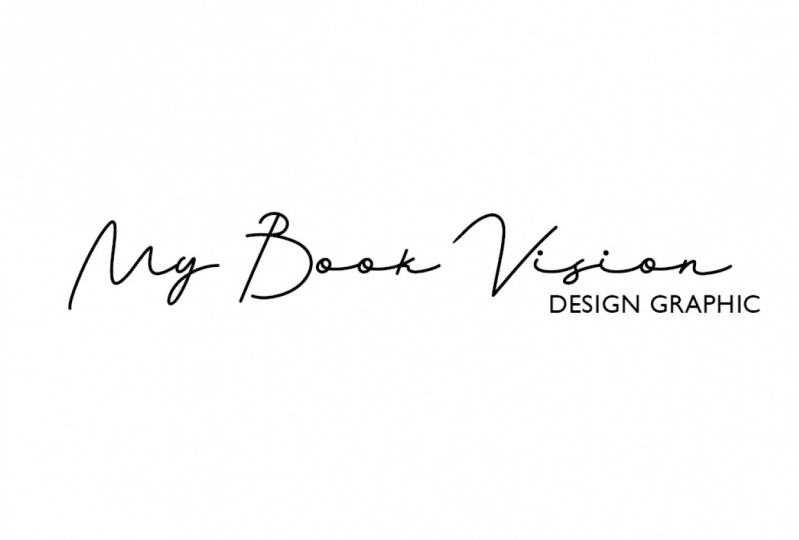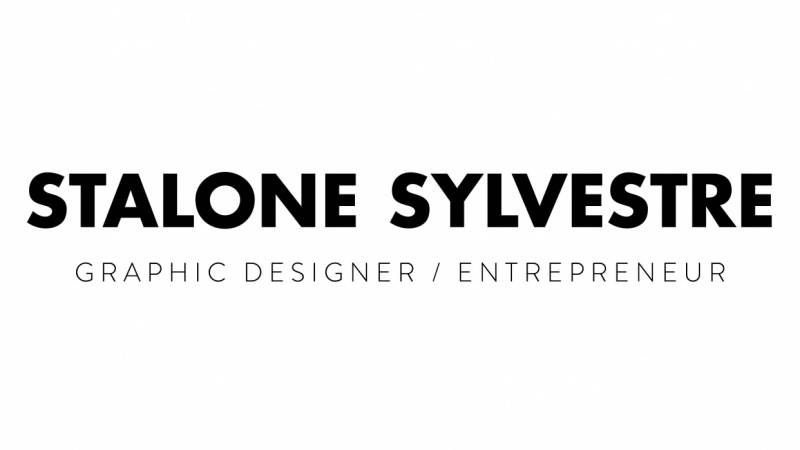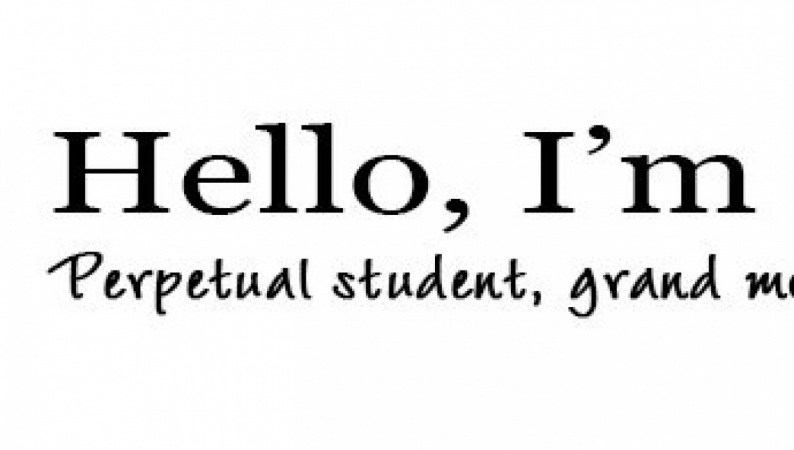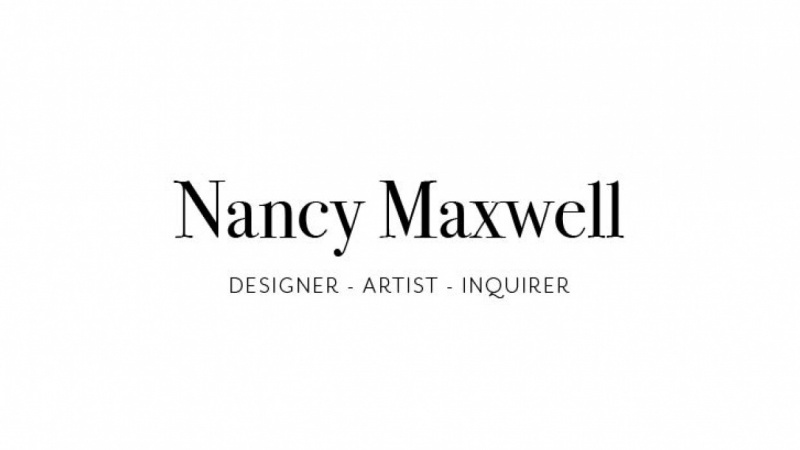
Dominando a tipografia 1: introdução ao contraste tipográfico
Apresentação e visão geral da série
Encontre algumas palavras para se apresentar
Crie designs impressionantes com contraste tipográfico
A tipografia é um dos principais componentes do design gráfico, e cometer erros é muito fácil. Mas também não é tão difícil acertar e fazer algo incrível! Nesta série vou explicar passo a passo todos os diferentes aspectos da tipografia e criar layouts eficazes que impactam o visitante. Amo uma boa tipografia e quero ver mais disso por aí.
Meu nome é Evgeniya Righini-Brand e sou uma designer gráfica com uma experiência extensa no trabalho com tipos em vários níveis diferentes e ensinando tipografia de nível universitário.
O que você vai aprender neste curso:
Neste curso, vamos dar uma olhada nos conceitos básicos da tipografia, princípios de contraste tipográfico e na seleção e combinação de tipos de fontes para transmitir a mensagem desejada. As habilidades de estilo que você vai obter através deste curso lhe permitirão fazer um trabalho simples baseado em texto e destacá-lo, seja ele uma apresentação, criação de uma página de título para seu trabalho acadêmico escrito ou a criação de imagens cativantes de capa para seus cursos ou projetos aqui na Skillshare ou em outras plataformas redes sociais.
A parte técnica desse curso abrange conceitos básicos de trabalho no Adobe InDesign, mas se você não tiver o InDesign instalado, não deixe de se inscrever, porque você pode praticar a composição tipográfica e as habilidades relacionadas ao estilo ensinadas neste curso no Adobe Illustrator, Photoshop ou qualquer processador de palavras padrão, como o Pages, Word ou até mesmo no Google Docs.
1. Apresentação e visão geral da série: Ei pessoal, isso é [inaudível] criativo. Bem-vindo à minha nova série sobre dominar a tipografia, na qual passarei passo a passo por todos os diferentes aspectos da tipografia, criando layouts eficazes e trabalhando de forma eficiente no Adobe InDesign, que é a minha principal escolha quando se trata de projetando este tipo. Se você quiser aprender do zero ou melhorar as habilidades existentes do InDesign, ótimo e se você não tiver a instalação do InDesign. Bem, não é o fim do mundo, porque muito do que eu vou cobrir nesta série é sobre estilo. Você pode experimentar a configuração de fonte no Adobe Illustrator Photoshop, ou mesmo em qualquer processador de alimentos padrão, se souber onde estão as ferramentas e o que deseja alcançar. Nesta série de aulas é realmente sobre a construção dessa compreensão de consciência. Todos os projetos de classe que serão configurados para você nesta série serão rápidos e divertidos e permitirão que você pratique novos aspectos da tipografia abordados em cada aula e produza algo útil que você pode expandir quando aprender mais. Na primeira aula, vamos começar aprendendo os conceitos básicos de tipografia, princípios de contraste topográfico e selecionar um tipo aparente de faces para refletir nossa personalidade. Vamos criar um crachá e crachá ou um cartão de introdução para nós mesmos, que no futuro você pode levar mais longe e desenvolver seu cartão de visita ou chefe de seu site ou blog. Por enquanto, apresente-se com estilo à comunidade aqui e em qualquer outra rede social, se quiser. Existem habilidades relacionadas que obtemos desta turma, lhe permitirão enfrentar eficazmente e fazer sobressair qualquer trabalho simples baseado em texto, seja uma apresentação, configurando a página de título para o seu trabalho acadêmico escrito ou fazendo imagens de capa cativantes foram aulas para projetos aqui em compartilhamento de habilidades ou em outro lugar nas redes sociais. Fico sempre feliz em responder a quaisquer perguntas, fornecer feedback e apoiá-lo a cada passo do caminho. Como eu já disse, se você não tem o InDesign, você pode definitivamente seguir essa classe e fazer o projeto de classe em qualquer outro software, então não deixe o software ficar entre você e aprendizagem como criar projetos tipográficos eficazes. Adoro conhecer novas pessoas e vou ficar muito animado para vê-lo na minha aula e ver como você pode se apresentar por meio de tipografia. 2. Interface e ferramentas básicas do InDesign: Vamos começar com os conceitos básicos de trabalhar no InDesign. Vamos criar composições tipográficas muito simples para esta classe. Então eu só vou cobrir aqui o que você vai precisar nesta fase, e eu vou expandir sobre isso em minhas futuras aulas da série. No Adobe InDesign, vá para o menu “Arquivo”, “Novo”, “Documento”. Agora, vamos preparar tudo rapidamente. Vamos compartilhar nosso trabalho on-line, então faz sentido definir a Intenção para Web e se você quiser desenvolvê-lo ainda mais para impressão, você sempre pode alterá-lo mais tarde. Por enquanto, vamos manter o número de páginas para um. Vamos trabalhar em diferentes designs do mesmo texto, então vamos apenas copiar páginas de dentro do documento à medida que avançamos para produzir diferentes variantes. Vamos trabalhar em páginas individuais em vez de espalhadas, por isso certifique-se de que as Páginas Viradas estão desativadas. Lembre-se sobre essa opção na configuração do documento. Na minha experiência, é algo que as pessoas esquecem facilmente. Se você precisar de uma simples apresentação ou documento de uma página ou slide de cada vez, não use Páginas opostas. Mas se você estiver trabalhando em algo semelhante a um livro que tenha duas ou mais páginas na página espelhada, então você precisará ativar as Páginas opostas. Vamos definir o tamanho da nossa página para algo como 1200 por 1200 pixels, isso é bastante grande um quadrado e por isso não temos distração pelas proporções da página e seria de boa qualidade quando exportamos para postar online. Então vamos ter apenas uma coluna aqui, não precisamos de mais para esta tarefa. Certifique-se de que você está alterando todas as margens ao mesmo tempo, clique neste botão de link para tornar todas as configurações iguais e defina margens como 100 pixels. Não precisamos fazer nada com configurações de Sangramento e Slug para esta classe, pois não estamos imprimindo. Então aqui estamos, clique em “Ok” para criar um novo documento. Vamos salvar imediatamente este documento para que não precisamos preocupar com isso mais tarde e basta clicar em “Salvar” ou “ Command S” ou “Control S” no Windows de vez em quando enquanto estamos trabalhando para que nosso arquivo seja sempre copiado. Trabalhando com o InDesign, é muito importante estar bem organizado para que você não perca nenhum material usado no documento. Nesta classe, nós não vamos ter nenhum arquivo vinculado, então nada com que se preocupar realmente, mas ainda é uma boa prática ter uma pasta separada para o projeto e um nome pesquisável para o arquivo. termos de formato, estamos salvando um formato de documento nativo do InDesign e, aqui, você pode ver que não há muitas opções de formatos para escolher de qualquer maneira. Documento do InDesign, que é o que é usado na maioria dos casos, formato de modelo do InDesign se você precisar ter um modelo para vários documentos e apenas um formato legado para algumas versões anteriores do InDesign. Clique em “Salvar” e vamos começar a trabalhar. Geralmente, a interface do InDesign é muito semelhante ao Illustrator e ao Photoshop, com painéis de ferramentas aqui no lado esquerdo, acesso rápido e painel específico de ferramentas na parte superior e todos os outros painéis de sua escolha no lado direito. A diferença está em algumas ferramentas e alguns painéis, e nós vamos cobrir esses passo a passo em cada classe da série. Com o nosso documento aqui, vemos os limites da página e a borda da página em torno dela. Se você estiver familiarizado com o Illustrator ou o Photoshop, então você pode ver que é uma lógica bastante semelhante. Aqui, temos uma página e no Illustrator, é um quadro de arte e uma tela no Photoshop. Todos eles especificam o formato do seu trabalho. Na página, temos este quadro magenta que define as margens que decidimos ter para o conteúdo. Os painéis de trabalho exibidos são determinados pelo espaço de trabalho que você está usando, o mesmo que em todos os outros programas da Adobe. Há várias predefinições de espaço de trabalho no InDesign e você pode escolher uma que melhor se adapte ao seu projeto. Para esta aula, vai ser tipografia. Você pode configurar seu próprio espaço de trabalho com as ferramentas e os painéis que você precisa, e salvá-lo como predefinido, se quiser. Eu vou usar espaço de trabalho tipografia nesta classe e apenas personalizá-lo rapidamente adicionando painel de alinhamento. Agora estou pronto. Também semelhante ao Photoshop e ao Illustrator, há vários modos de exibição: Normal, que mostra todas as guias, margens e dois-pontos, TextBoxes e threads, e todos os objetos em qualquer lugar na placa de rosto, este é um padrão que você vai usar a maior parte do tempo. Em seguida, há um modo de visualização que mostra apenas objetos imprimíveis na página, modo que todas as guias e todos os objetos além dos limites da página estão ocultos. Este vai ser um segundo modo de visualização mais comumente usado e para alternar entre esses dois modos, você precisa pressionar “W”. Apenas certifique-se de que você não está digitando em algum lugar em vez de usar Type Tool, então cuidado com a ferramenta em uso. Outro modo de visualização útil é a apresentação que coloca a página espalhar script completo. Pressione “Shift” e “W” para entrar e sair dela. Você também pode alternar entre modos de exibição usando esses botões no painel de ferramentas. Há mais dois modos de visualização para mostrar nas áreas de Bleed e Slug para impressão, mas falaremos sobre isso em outro momento. No InDesign, o conteúdo dos documentos é organizado usando o painel Páginas. Aqui você pode adicionar, remover, ajustar e reordenar todas as páginas do documento. Certifique-se sempre de que a página na qual pretende trabalhar está seleccionada. Você verá esse tipo de sobreposição de cor sobre a página e o número será destacado. Por que é importante? Bem, além do óbvio, há essa coisa complicada aqui acima de suas páginas de documentos que se chama A-Master. Mestres são modelos para suas páginas. Você pode ter um número deles para diferentes tipos de páginas e eles basicamente definem o tamanho da página que o layout guia, como colunas e linhas de sua grade, e permitem que você insira automaticamente elementos repetitivos como números de página, ou até mesmo configurar o layout TextBlock. Então, se você está trabalhando em livro de 100 páginas, você não precisa copiar e colar texto em cada menu de página. No topo de cada página do documento, você verá um marcador mostrando qual mestre é aplicado a esta página. Como aqui, há uma letra A para Mestre A. Para esta classe, não vamos nos preocupar com mestres, mas precisamos ter certeza de que estamos trabalhando em páginas de documentos reais em vez de em um mestre, então clique duas vezes em sua página para trabalhar com ela. Há também um painel de camadas aqui que, em essência é semelhante ao do Illustrator ou no Photoshop. Mas ao contrário desses dois programas, aqui, você não precisa que ele esteja aberto a maior parte do tempo. Na minha prática, eu raramente vou ao Painel de camadas no InDesign, talvez seja devido ao fato de que eles trabalham em layouts bastante minimalistas com elementos mínimos sobrepostos ou talvez seja porque eu faço a maioria das coisas com o , bem, eu não tenho certeza, mas você precisará ter em mente que cada página no InDesign tem seu próprio conteúdo de camadas, e você só pode ver as camadas da página selecionada em vez de todo o documento. Na verdade, é uma coisa muito boa porque não há desordem e você só pode ver o que você precisa ver. Para esta classe, você precisará usar apenas duas ferramentas do painel de ferramentas. Uma é a ferramenta Seleção que é praticamente a mesma que no Illustrator e aqui, ela é usada para selecionar objetos, TextBoxes, e assim por diante. A segunda ferramenta que você precisará para esta classe é a Ferramenta de texto, que é muito semelhante à do Illustrator ou do Photoshop, mas com uma grande diferença. Como o InDesign se destina a trabalhar com um grande corpo de texto, você só pode usar o tipo dentro de TextBoxes ou, se precisar dele para fins mais decorativos, você também pode definir o tipo em caminhos. A maior parte da funcionalidade do InDesign, de uma forma ou de outra, gira em torno de TextBoxes, que você descobrirá em breve. Então, aqui, para começar a digitar, você deve primeiro desenhar uma caixa com a Ferramenta Tipo e, em seguida, digitar dentro dela. No Photoshop e no Illustrator, basta clicar em algum lugar com a Ferramenta de texto e começar a digitar. Aqui, não funciona assim, então é algo para se acostumar. Vamos desenhar uma caixa de texto para o nosso texto futuro seguindo as guias de margem. Agora, ainda tendo minha caixa de texto selecionada com a ferramenta de texto, posso começar a digitar dentro dela. Então precisamos decidir o que realmente queremos digitar aqui. Eu vou passar rapidamente por isso no próximo vídeo e então vamos começar a projetar. 3. Encontre algumas palavras para se apresentar: Para praticar habilidades abordadas nesta classe, criaremos uma tag com uma introdução pessoal. O objetivo é apresentar-se em poucas palavras com um estilo tipográfico que reflete quem você é e o que você é. Primeiro de tudo, precisamos descobrir o que nossas apresentações vão dizer. Vou digitar aqui meu nome e algumas palavras que descrevem quem eu sou. Dependendo do que você se identifica, como você pode querer incluir sua profissão, nacionalidade, status familiar ou qualquer outra coisa que você acha que é importante. Por exemplo, se você é um amante de gatos, vegetariano, corredor de maratona, ou qualquer outra coisa ao longo das linhas, conte-nos sobre isso. Para mim, vou escrever que sou designer gráfico, fotógrafo e explorador. Gosto de viajar muito, ver coisas novas, ir a lugares diferentes, não importa onde, longe ou perto. Há um monte de outras coisas sobre mim, por exemplo, eu sou apaixonado por cozinhar, eu amo esportes, eu faço mountain bike, eu tenho um cinto preto em taekwondo desde minha adolescência, eu amo acampar, e um monte de outros coisas. Mas ser um designer gráfico, para mim é um estilo de vida e ser fotógrafo e explorador são outros dois pontos principais sobre mim neste momento da vida. Então vou digitar meu nome aqui. Você pode colocar seu primeiro nome, seu nome completo, depende de você. Eu também vou torná-lo um pouco mais pessoal usando a versão curta do meu nome. Eu sou originalmente da Rússia e eu tenho um nome russo, ou melhor, um nome grego, [inaudível] mas para pessoas de língua inglesa, parece ser bastante difícil de pronunciar. Eles são racionalmente, e eu pessoalmente não gosto da versão inglesa do nome, ou da maneira como as pessoas o pronunciam do jeito que meu nome é escrito. Gostaria de manter a versão curta que é mais Inglês amigável, Jenya, que é semelhante a Jenny, mas um pouco diferente, e eu também vou adicionar uma saudação aqui apenas por causa de chamar a atenção dos espectadores. Você também pode trocar seu nome e sua descrição, se quiser. Eu estava trabalhando nos projetos da classe, ver o que funciona melhor para você, e se você precisa mudar seu texto, adicionar ou remover algo enquanto trabalha, então vá em frente. Agora, podemos começar a escrever nossos textos de várias maneiras diferentes para destacá-lo e é sobre isso que o próximo vídeo é sobre. 4. Crie designs impressionantes com contraste tipográfico: Bem, no momento parece bem simples, então eu preciso estilizá-lo. Para esta tarefa, não quero que se preocupe com alinhamento e composição. Selecione o texto e vamos apenas alinhá-lo centralmente. Você pode fazê-lo aqui no painel superior, ou você pode ir para o painel de parágrafos e fazê-lo lá, se quiser. Também no painel de parágrafos, é uma boa idéia ativar toda a hifenização automática para esta tarefa. Em seguida, vamos usar a ferramenta de seleção, seleciona a caixa de texto e os textos de linha para o centro vertical da caixa. Agora, isso já está um pouco melhor. Nesta aula, quero que você aprenda a criar fortes composições tipográficas e pares de tipos com o mínimo de destruição. É por isso que trabalharemos apenas com texto preto sobre fundo branco e sem outras cores. A comunicação será exclusivamente para o tipo. A cor preta é uma cor padrão no design, então você não precisa mudar nada. Ter todos os textos em um estilo uniforme faz com que pareça calmo e estável e é apropriado quando você está trabalhando com um grande corpo de textos ou leitura prolongada como um em um livro ou em outros casos em que este modo é realmente o que você quer para transmitir. Mas, na maioria das vezes, o caso é que o texto contém informações de diferentes tipos e diferentes níveis de importância. É por isso que você precisa estabelecer o que é chamado de hierarquia tipográfica para garantir que a exibição pode facilmente navegar pela quantidade em ordem de importância. O olho humano é naturalmente atraído para contrastar. Contraste, ou falta dele para esse assunto, dá ao design um personagem e, de uma forma ou de outra, há sempre certo nível de contraste em qualquer trabalho. Pode ser contraste entre formas de letra e espaço em branco, letra e outras formas de letra, formas letra e imagem, e assim por diante. Uma forte hierarquia demográfica faz um design destacado. Em primeiro lugar, porque os contrastes atraem a atenção e em segundo lugar, porque desta forma o espectador pode ler e compreender muito rapidamente a parte mais importante do que se trata. Nesta aula, vamos dar uma olhada em como o contraste pode ser construído entre dois pedaços de textos, diferentes em propósito. Todos nós estamos acostumados a ver manchetes grandes e negrito, corpo de texto regular e pequenas legendas ou créditos. Tudo faz sentido porque diferentes tipos de informação são percebidos de uma forma diferente e têm funções diferentes. Neste projeto de classe, eu quero que você considere a função de dois bits de texto, e ele está aberto à sua interpretação e pode haver variações na maneira como você deseja abordá-lo. No geral, o objetivo é apresentar-se e refletir suas qualidades e, claro, chamar a atenção. Mas como você quer alcançá-lo, eu deixo para você decidir. Vamos dar uma olhada em algumas, mas não todas as maneiras de alcançar o contraste tipográfico, que você precisará experimentar e ver como ele funciona e como ele muda a percepção de seus textos. Para todos esses ajustes, vamos usar o painel de caracteres. Para começar, precisamos escolher um tipo de letra que reflita nosso personagem. Estou usando o Adobe Typekit e acho isso extremamente útil e considerado uma das melhores ofertas de assinatura da Creative Cloud. Se você é tão sortudo quanto eu, há um monte de tipografia para escolher. Caso contrário, existem várias opções diferentes onde você pode obter boas fontes, pagas e gratuitas para uso pessoal. Coisas para as bibliotecas de fontes estão incluídas na descrição do projeto de classe e nas notas para este vídeo. Vou procurar algo simples para começar. Dependendo do que você deseja alcançar, você precisará decidir qual tipo de letra representa você melhor. É sério e clássico? Ou é elegante e sofisticado? É contemporâneo, amigável e descontraído? Ou é tão amigável, mas simples e direto ao ponto sem qualquer frescura? É algo mais astuto ou caligráfico? Ou talvez seja um pouco mais hipster? O que você é? Você tem que olhar no espelho metaforicamente ou literalmente se isso ajuda e decidir. Se você entrar em tipos de letra do kit, visualize seus textos que você precisa definir lá e escolha os tipos de letra desta forma. Como alternativa, percorra a lista de tipos de letra no painel de caracteres no InDesign. Você pode escolher um tipo de letra, procurando a lista ou selecionar o campo e mantendo pressionada a tecla Shift e usar uma seta, percorrer toda a lista em ordem. Este processo é praticamente o mesmo, quer esteja a utilizar qualquer outro programa da Adobe, Microsoft Word, páginas da Apple ou qualquer outra coisa em que possa estar a trabalhar. A próxima coisa que precisamos definir é o tamanho do tipo. Você pode fazer isso aqui no painel de caracteres. Bem, em primeiro lugar, faça o tipo grande o suficiente para ser legível em seu projeto de compartilhamento de habilidades. Para o tamanho da página que estamos usando, não vá abaixo, eu diria que cerca de 20 pontos para ser seguro. Caso contrário, será muito difícil de ler. Isso vai fazer. Agora vamos para o painel de páginas e copie esta página quatro vezes. Temos o mesmo ponto de partida para cada um dos princípios de contraste, testes de aplicações. Vamos voltar para a página 1. Agora, nós temos ambos os pedaços de texto do mesmo tamanho e por causa disso, eles perceberam da mesma maneira, mas queremos adicionar um pouco de contraste e fazer, digamos, o nome se destacar um pouco mais. Neste ponto, você pode querer alterar a configuração de iluminação aqui para controlar a distância entre suas linhas de texto, mas eu vou falar sobre isso com mais detalhes um pouco mais tarde neste vídeo. Ter um tamanho de tipo diferente é a primeira maneira de alcançar o contraste tipográfico. Brincar com ele até obter o resultado que você está feliz com. Se você quiser ter todas as suas variantes para comparação, duplique esta página ao tentar variantes em suas cópias. Font-weight é a próxima coisa que pode nos ajudar a criar contraste tipográfico. Diferentes tipos de letra podem ter um número diferente de maneiras disponíveis, mas a maioria dos tipos de letra profissionais, terá mais do que suficiente indo de fino, leve e regular para médio negrito e preto e alguns têm ainda mais do que isso, há muitas opções para escolher. Vamos para a segunda página original no documento onde tudo ainda é do mesmo tamanho e aplicar maneiras diferentes a dois pedaços diferentes de texto para ver como isso afeta a percepção do texto. Texto em negrito grita textos mais altos e leves, por outro lado, é mais silencioso e moderado. Experimente algumas combinações diferentes para ver o que é melhor para você. Novamente, copie a página quando necessário se quiser manter todos os seus experimentos. Volte para a página original número três, e agora vamos dar uma olhada em como fórum das letras pode criar contraste tipográfico. Fórum refere-se se a fonte é romana ou itálico, minúsculas, maiúsculas ou minúsculas. Para alterar o estilo de romano para itálico, use este menu suspenso sob o tipo de letra. Para usar todas as maiúsculas ou minúsculas, você deve ir para o menu suspenso no canto superior direito do painel de caracteres e escolher a opção desejada lá. Experimente com o fórum, mas tenha em mente para não sobredosagem Itálico. maiúsculas e pequenas são boas para títulos curtos e Italic é normalmente usado para destacar algo, mas pode ser usado para adicionar um sentimento diferente, mais suave, elegante e potencialmente feminino, especialmente com Serif e laje serif tipo faces. Muitas vezes foi formado pai contraste romano com itálico ou romano com todas as tampas é mais do que suficiente. Novamente, volte para a página original Número 4 e vamos dar uma olhada em como a textura do livro didático geral ou linhas de texto individualmente podem ser alteradas. A textura pode ser normal, solta ou apertada. Para ajustá-lo, precisamos lidar com algumas configurações. Em primeiro lugar, ele é conduzido ou espaço de linha e altura da linha, que se refere à distância entre as linhas de base do texto, e você pode alterá-lo aqui. Normalmente, o valor de led é de cerca de 125-175 por cento do tamanho do tipo, mas depende da forma do tipo e geralmente o design que você pretende. Você pode brincar com ele e ver o que mais lhe convier. Além disso, você pode alterar o espaçamento entre a sucessão de caracteres, que é chamado de rastreamento, e estes também afetarão a aparência dos textos em geral. O espaço em branco com rastreamento mais solto, todos ecoam com um título em cria contraste dentro da linha de texto e faz com que pareça mais leve ou mais pesado, respectivamente, o que também ajuda a se destacar dos textos com rastreamento normal. Eu, pessoalmente, gosto de criar contraste usando legendas em maiúsculas como descrição secundária. Há rastreamento solto de cerca de 150-100 e emparelhamento com tipo negrito e maior. Com o latim e o rastreamento, tentarei evitar bater linhas ou letras juntas, pois isso afeta a legibilidade e legibilidade. Evite também ter rastreamento muito solto porque também torna difícil de ler quando as letras estão muito distantes e espaços entre as letras se tornam semelhantes aos entre as palavras. Neste ponto, eu também quero dizer algumas palavras sobre kerning, uma configuração que se refere ao espaço horizontal apenas entre pares de letras individuais, que pode ser problemático e parecer maior ou menor em comparação com o resto. No InDesign, você pode definir uma configuração de kerning global para o texto e escolher entre métricas, ópticas ou qualquer numérico. Estes levam em conta as configurações de kerning do tipo de letra. Normalmente, você escolheria métricas ou ópticas e, em seguida, ajustar pares problemáticos se houver alguma clicando entre duas letras, que precisam ser kerning e ajustando a configuração numérica aqui. Experimente todas as configurações de Latim e rastreamento diferentes para ver como isso afeta sua composição e ajuste o kerning quando necessário. Aqui, o começo divertido. Contraste de estrutura, que se refere ao contraste entre diferentes tipos de letra. Eu sei que é isso que você estava esperando. Vamos dar uma olhada na criação de contraste através da combinação de tipos de letra. Paring de tipos de letra permite que você os reproduza uns dos outros, e ao fazer isso, adicione mais personagens ao seu design. Existem regras diferentes sobre paring de tipos de letra. Nesta aula, eu quero me concentrar no contraste como princípio. Mas se você quiser saber mais sobre outras abordagens, você pode seguir os links nas notas para este vídeo e na descrição do projeto da classe. Ao aparar as fontes, você precisa pensar sobre como elas funcionam visualmente e conceitualmente, porque algumas fontes simplesmente não se encaixam devido à forma como foram criadas, são conotações estilísticas fortes, ou simplesmente visualmente. Normalmente, você combinaria algo razoavelmente neutro com outra coisa com um pouco mais de caráter, como sans serif com serif, sans serif com serif laje, sans serif com tipografia decorativa ou qualquer outra coisa ao longo das linhas. A chave é mantê-lo simples e encontrar o equilíbrio certo. Começando com um tipo de letra que você já escolheu, encontre outro que transmita seu personagem e funcione bem com sua primeira escolha. Em seguida, experimente mais combinações de outros tipos de letra para ver como eles expressam sua identidade. Para ajudá-lo com o processo de seleção, coloquei alguns links para algumas grandes mostras de emparelhamento de fontes nas notas e na descrição do projeto da classe. Se você precisa de tipografia, uma boa maneira de começar é encontrar o que definitivamente funciona, e construir seu próprio trabalho sobre ele. Então, a confiança e a sensação para os tipos de letra virão. Estes são os poucos princípios simples de criar contraste tipográfico, e como agora você os conhece separadamente, é hora de combiná-los e ver o que mais você pode conseguir tendo, por exemplo, dois diferentes tipos de letra e definindo-os em peso , tamanho e caixa diferentes, e com o valor de rastreamento diferente. Esta é a parte mais emocionante, porque agora você tem tantas coisas para brincar. Mas também é importante lembrar que você não precisa de todas essas coisas e que você pode alcançar um resultado forte apenas alterando um dos aspectos. Isso é tudo para a tarefa. Agora, salve o arquivo uma última vez e assista ao próximo vídeo onde eu passarei rapidamente pelas configurações de exportação para esta tarefa e compartilhando seu trabalho on-line. 5. Exportar, compartilhar e conclusão: Para ter todas as suas páginas como arquivos de imagem para carregar on-line, precisaremos exportá-las como JPEGs ou PNGs se desejar. Selecione se deseja exportar um intervalo específico de páginas ou todas elas. Selecione páginas de exportação, pois não temos páginas espelhadas de qualquer maneira. Defina a qualidade para o máximo e 300 PPI, que tudo fique bem em todas as telas de retina, mesmo independentemente do fato de que nossas páginas já são muito maiores do que o tamanho da saída pretendida. Mantenha essas duas configurações aqui assim e clique em Exportar. Em outra nota, que não tem nada a ver com esta classe, mas ainda assim, quando você está exportando trabalho para impressão, exportação como PDF ou em alguns casos como EPS e nunca exportar apenas os arquivos como JPEGs, PNGs, ou como é para fins de impressão, porque desta forma você vai perder a qualidade perfeita do seu tipo. Além disso, há uma função muito útil que permite empacotar o projeto e todo o seu conteúdo. O que ele faz é que ele coleta todos os materiais usados no documento e o coloca juntos em uma pasta. É muito útil se você precisa se mover para outro computador ou dar o projeto para outra pessoa. Ou se você estiver muito desorganizado e colocado imagens de todo o lugar, em vez da mesma pasta com o arquivo do InDesign. Mas isso é apenas para que você saiba que essa opção existe, e vamos abordá-la com mais detalhes em algumas lições futuras onde seria necessário. Agora, vá em frente e compartilhe seus resultados na seção do projeto para a classe e nas mídias sociais, se você quiser. Tag atitudes, habilidades e dominar a tipografia no Instagram, para que eu possa acompanhar você lá também e ver a reação de seus seguidores. Aqui estamos, espero que tenham gostado desta aula e aprendido algo novo. Estou ansioso para ver seus projetos e ver como você pode se apresentar como tipografia. Se você tiver algum tipo de perguntas, me dê um grito, e eu ficarei feliz em comentar e fornecer feedback. Obrigado por se inscrever nesta aula, e espero vê-lo em breve na minha próxima aula.